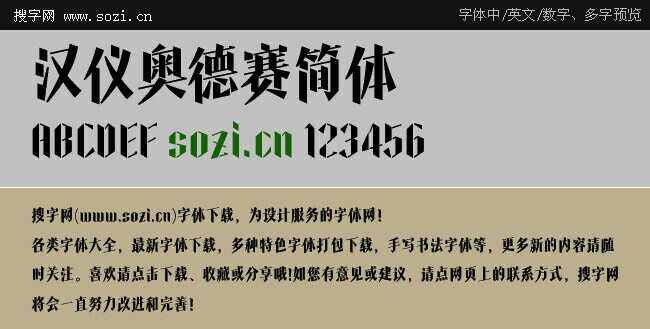
漢儀奧德賽簡體
搜字網(wǎng)給大家提供一款漢儀奧德賽簡體中文字體下載,漢儀奧德賽體是一套廣告POP字體,字體筆觸鮮明,字形夸張醒目,并向右上側(cè)傾斜,排列起來具有很好的視覺感。適用于畫冊設(shè)計、海報設(shè)計、包裝設(shè)計等場合使用。(本字體為個人非商用版,如需要商用請聯(lián)系漢儀公司購買版權(quán))